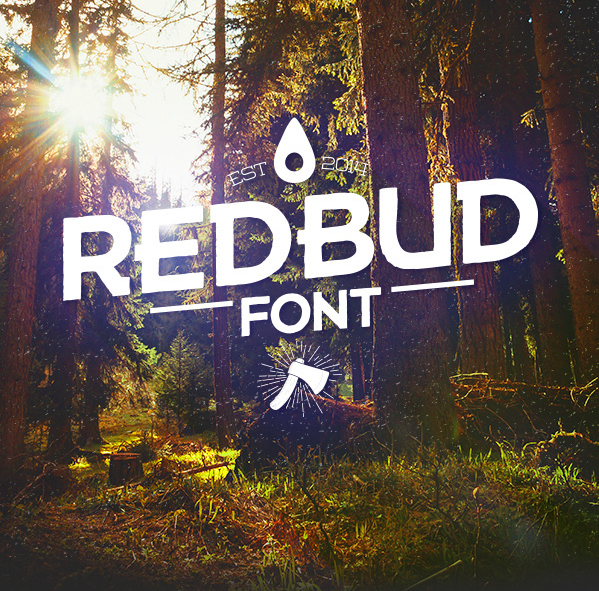
A REDBUD Font é uma elegante escolha para designers que buscam um estilo moderno e funcional. Esta fonte sans-serif foi criada por Hamilton, oferecendo linhas retas e leves que se destacam por sua facilidade de leitura. Com uma estrutura simples mas atraente, ela permite que os textos fiquem claros em qualquer formato visual, seja um blog informativo ou um site profissional. Seja para headlines, parágrafos ou outros elementos gráficos, REDBUD oferece o tom certo e a precisão necessária para manter sua mensagem ativa e interessante. Ideal tanto para quem busca uma fonte de bom gosto quanto para designers que valorizam o conforto visual em uma era cada vez mais digital.